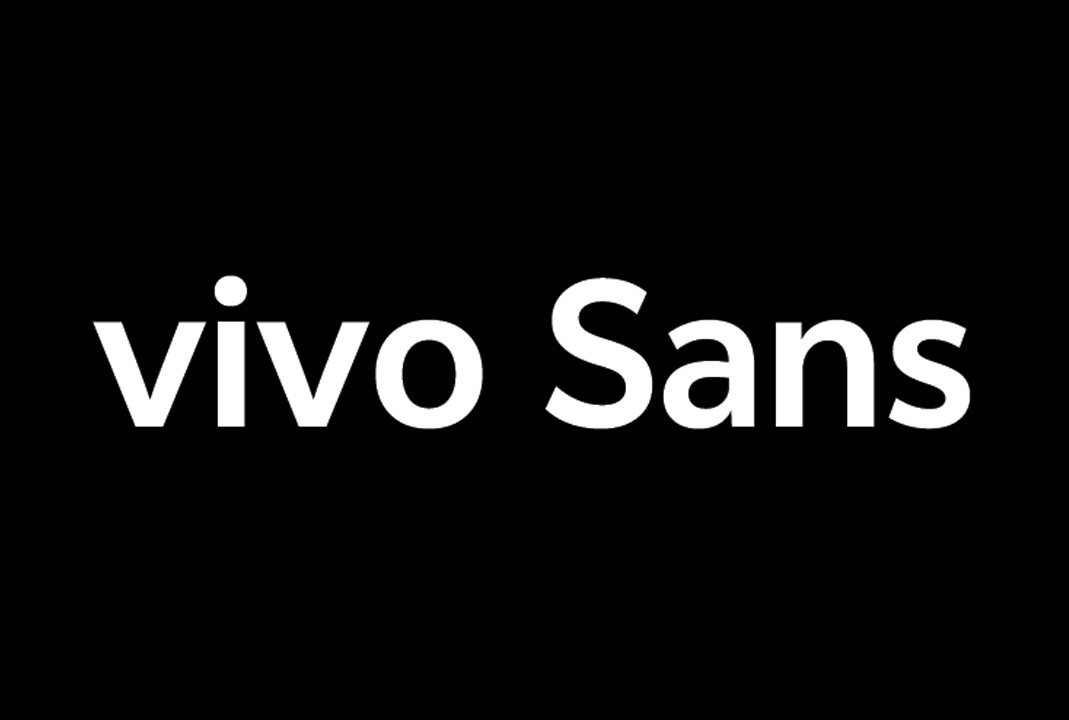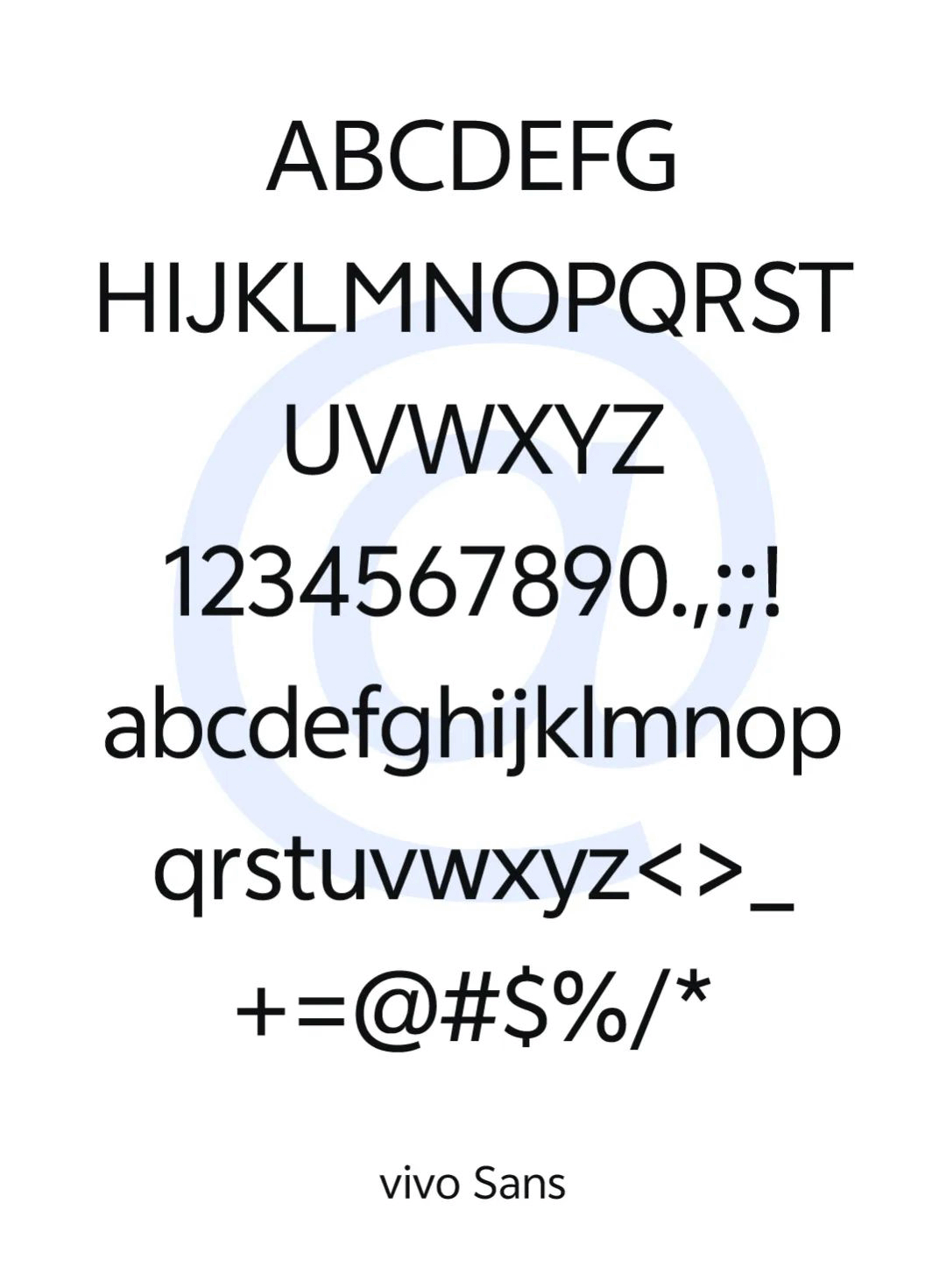
vivo Sans字体是 vivo 官方发布的一款免费商用中文字库,该字体(vivo Sans)由vivo与方正字库携手设计,设计核心回归文字的本质,注重简洁与易读性,摒弃过多的装饰细节,专注于精细的结构优化。让用户更好地专注于内容本身,为提供清晰易读的阅读体验。
vivo Sans 字体字符覆盖广泛,充盈挺括、饱满舒张,简约现代,字间距节奏均匀,整体风格传递出稳重平衡、中性普适的风格特质,适用于多种场景和使用需求。可用于各类场景。